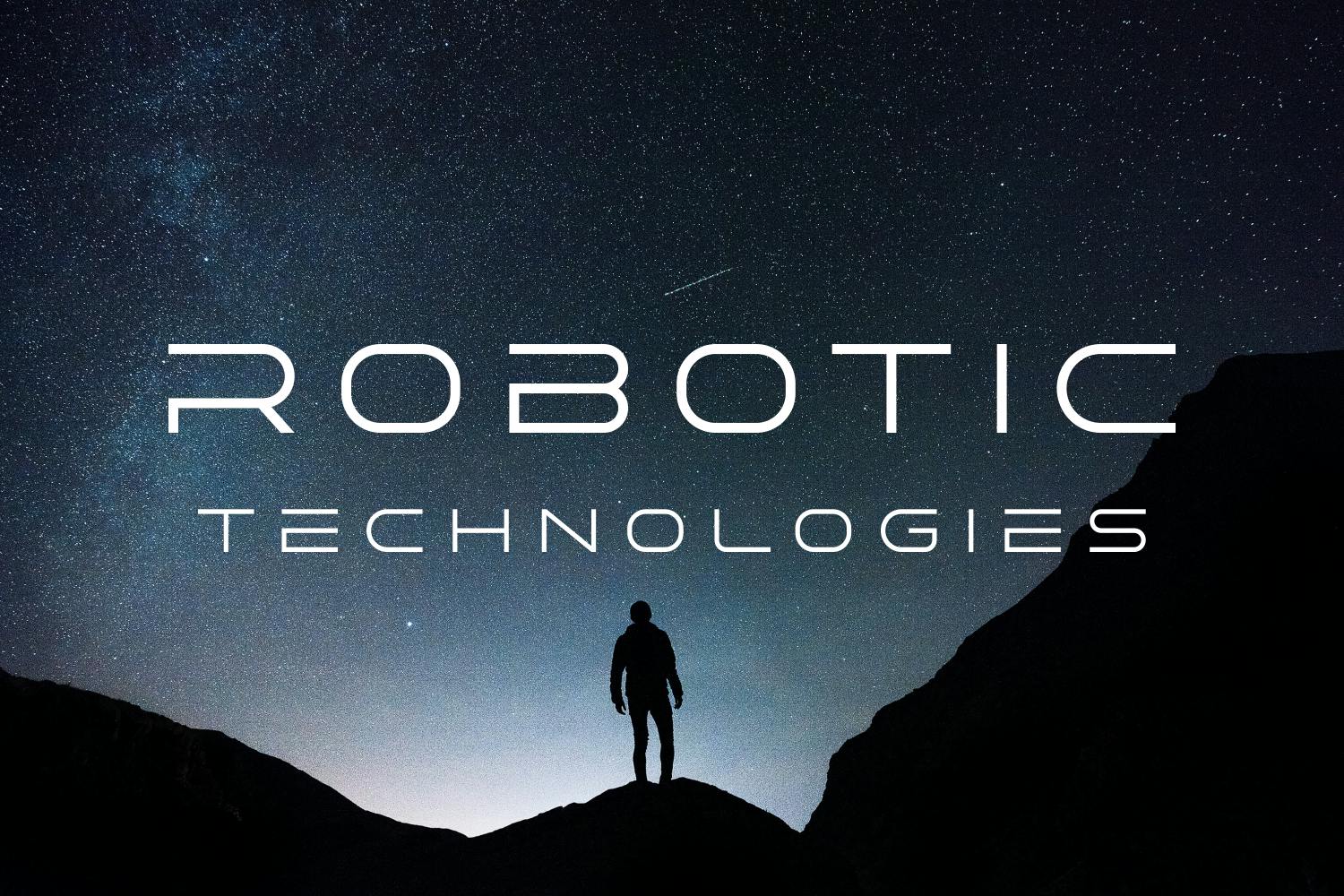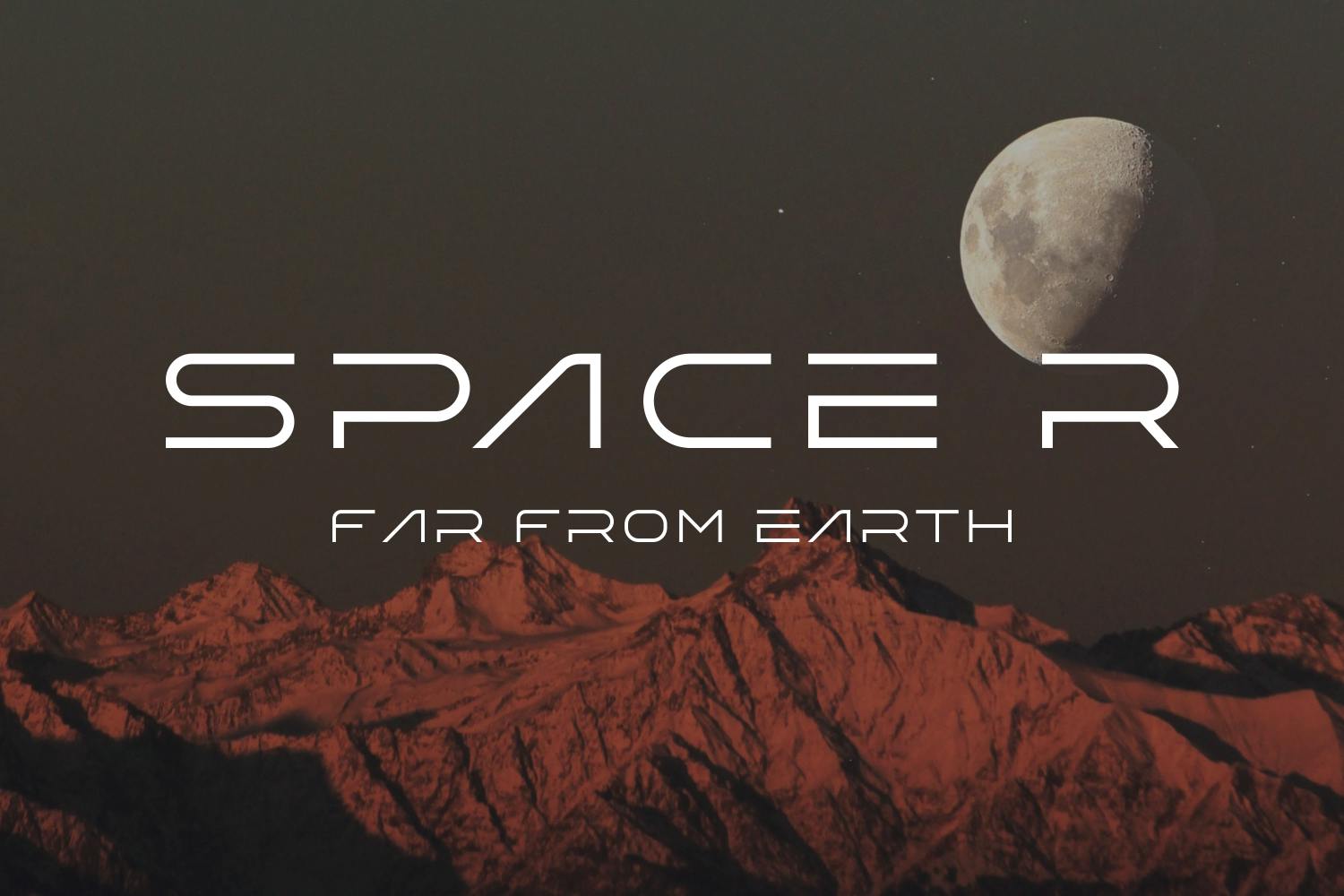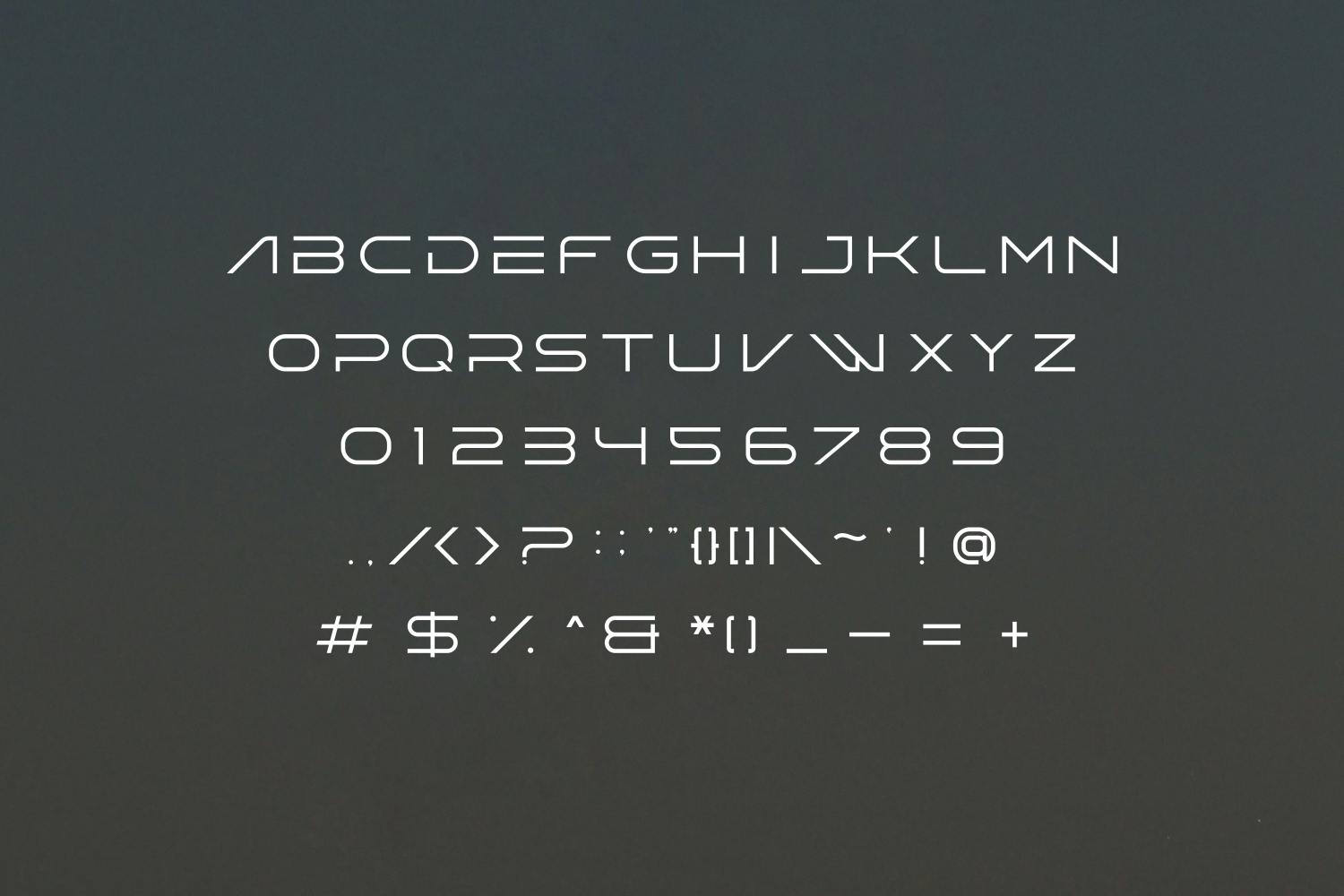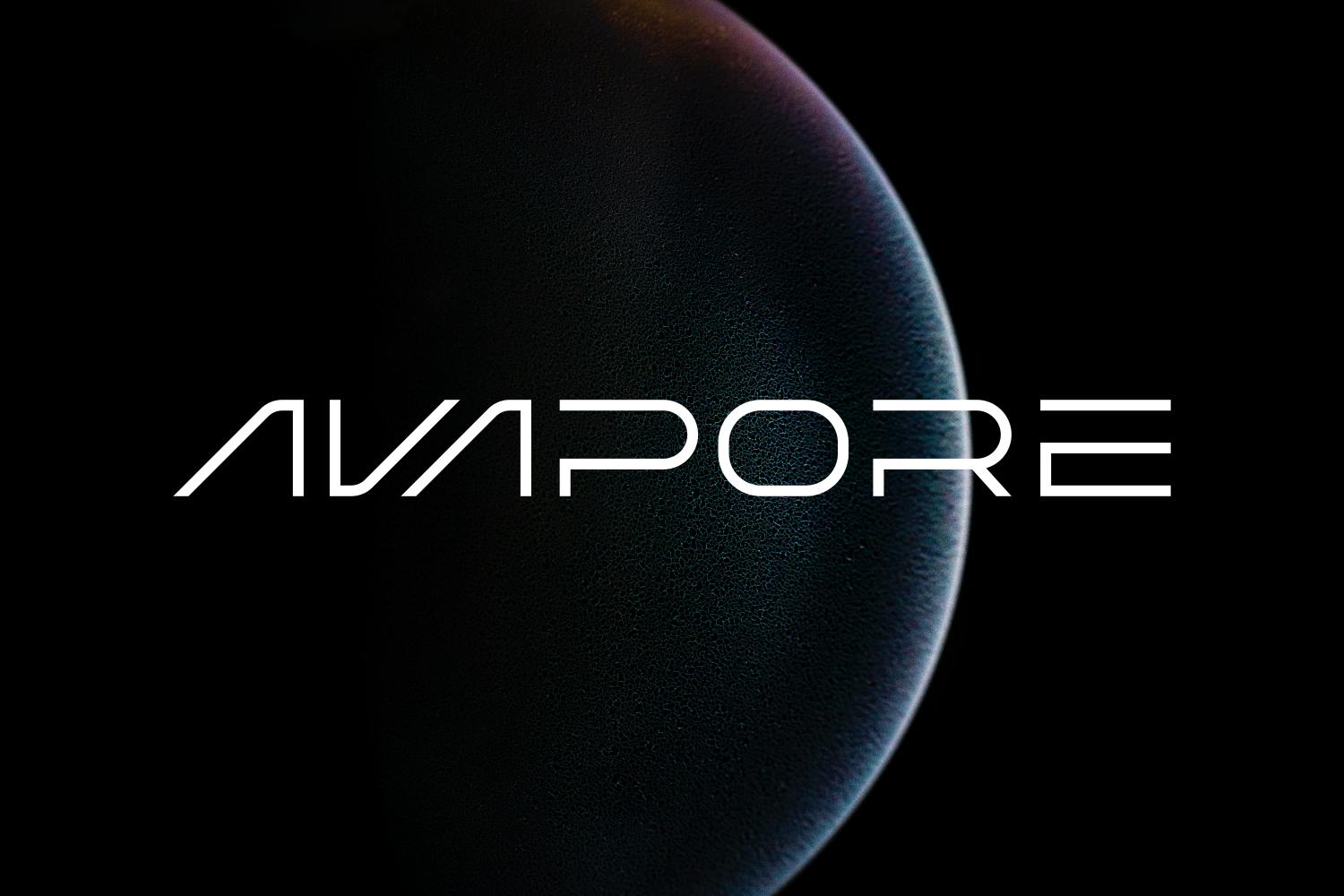
دانلود فونت مدرن Avapore با طراحی جذاب
Avapore modern font
فونت Avapore با طراحی مدرن و کاربردی، انتخابی ایده‌آل برای پروژه‌های شماست.
فونت Avapore یک نوع خط مدرن و عریض است که به عنوان یک راه‌حل برای برندینگ و ویرایش طراحی شده است. این فونت به گونه‌ای طراحی شده که بسیار انعطاف‌پذیر و چندمنظوره باشد و می‌تواند در پروژه‌ها و رسانه‌های مختلف مورد استفاده قرار گیرد.
• مناسب برای طراحی‌های برندینگ و ویرایش
• قابل استفاده در پروژه‌های گرافیکی مختلف
• طراحی مدرن و جذاب
• انعطاف‌پذیری بالا در استفاده